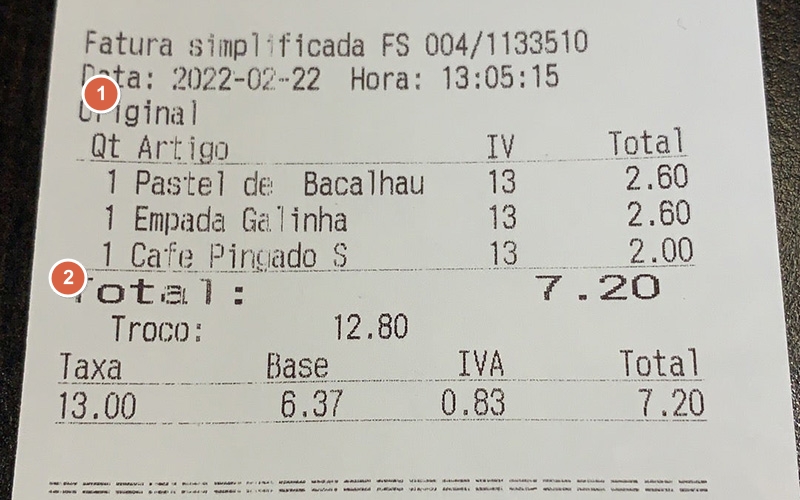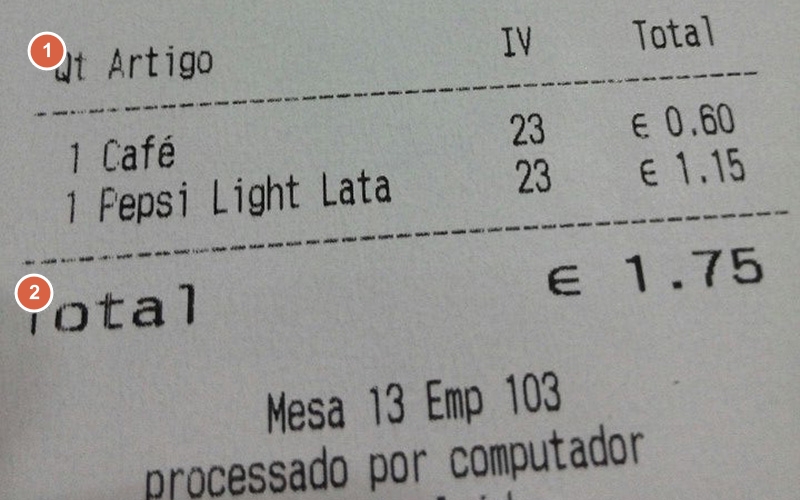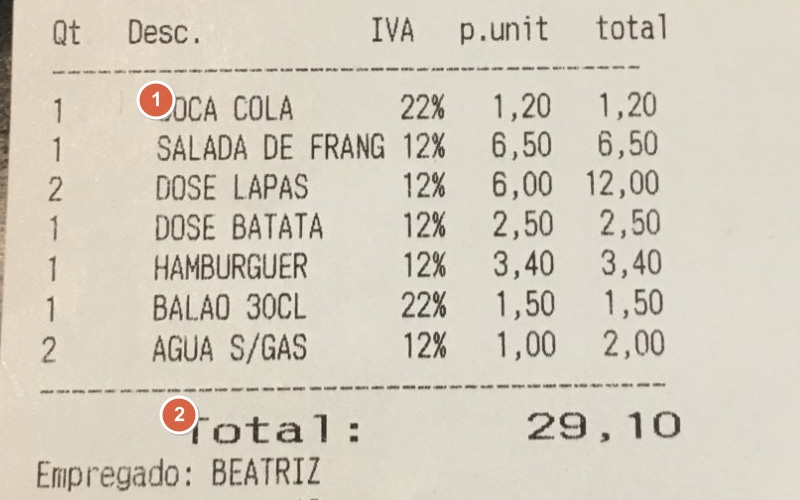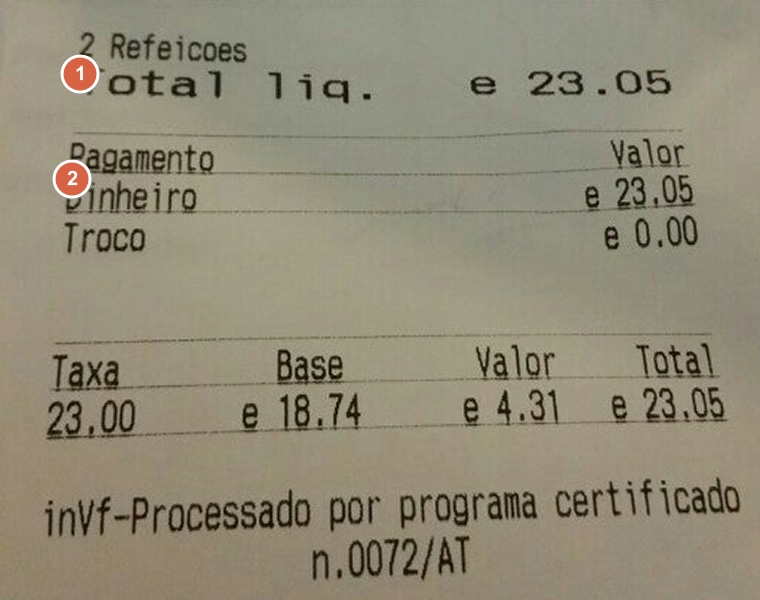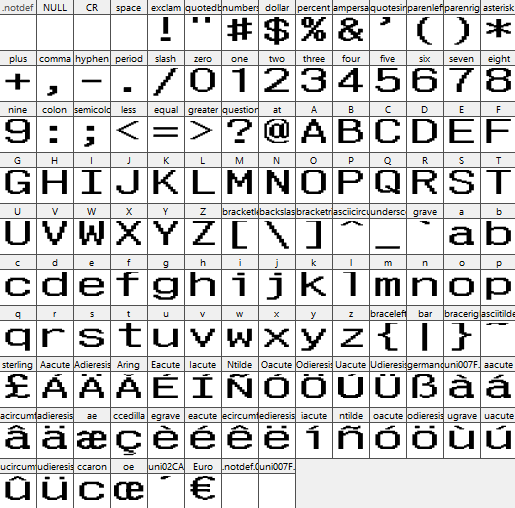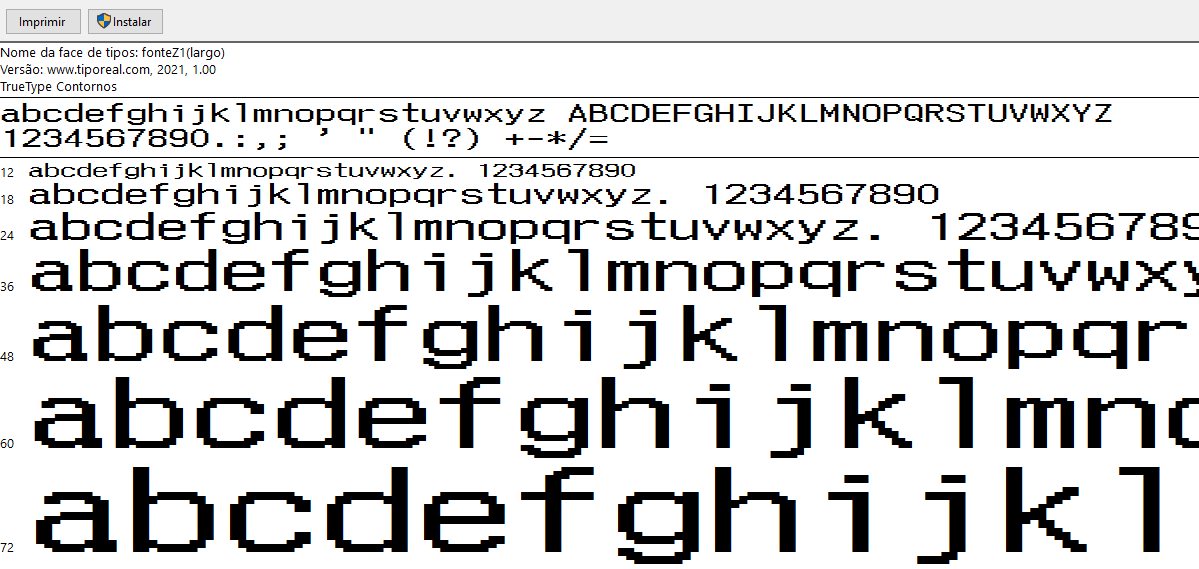
Amostra impressa da fonte para fatura simplificada de um pastelaria em Portugal (❶fonteZ1 ❷fonteZ1-largo)⤴
Amostra impressa da fonte para fatura simplificada de um pizzaria em Portugal (❶fonteZ1 ❷fonteZ1-largo)⤴
Amostra impressa da fonte para fatura simplificada de um restaurante em Portugal (❶fonteZ1 ❷fonteZ1-largo)⤴
Amostra impressa da fonte para fatura simplificada de um restaurante em Portugal (❶fonteZ1-largo ❷fonteZ1)⤴
Todos os personagens⤴
O que parece quando aberto com o visualizador de fontes padrão do Windows⤴